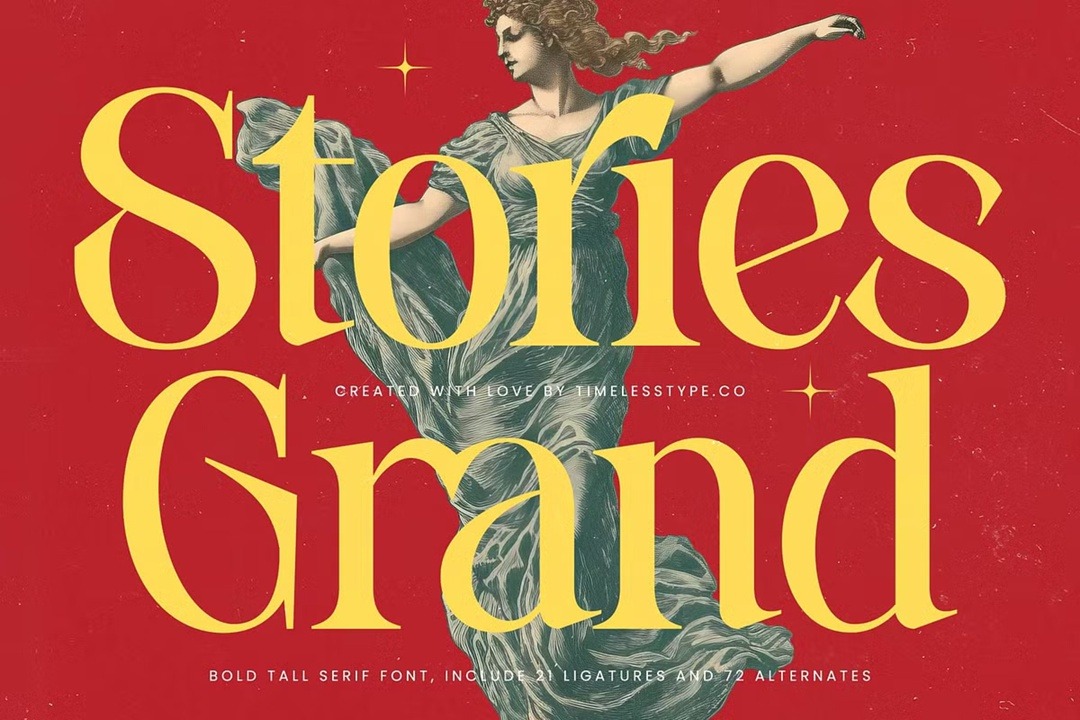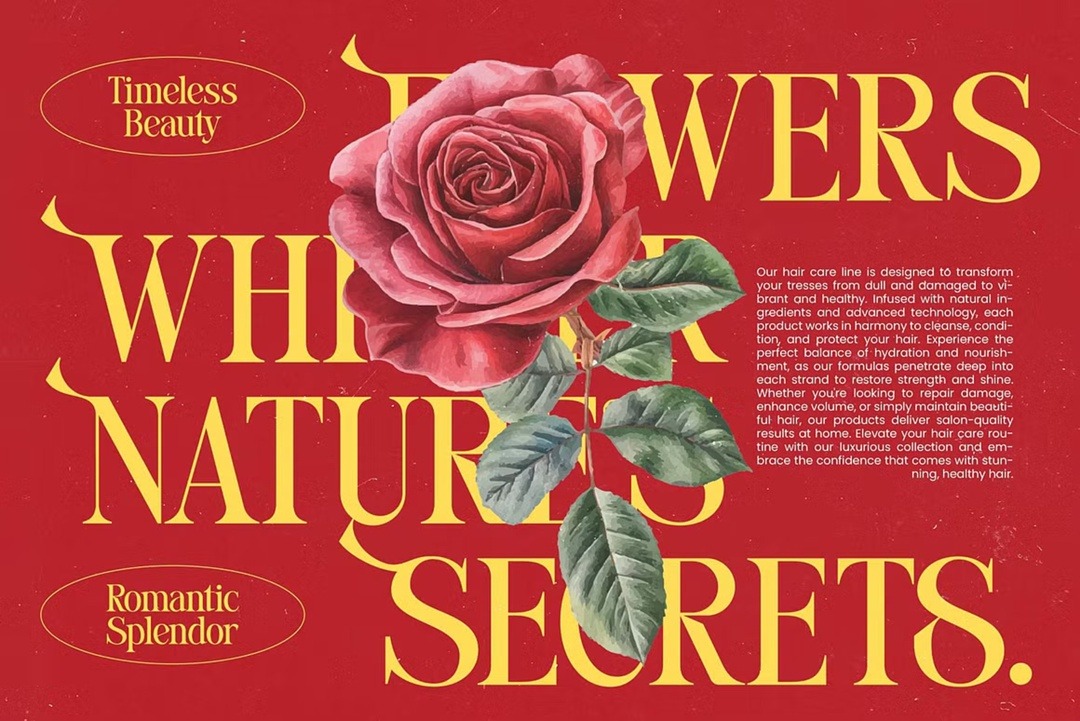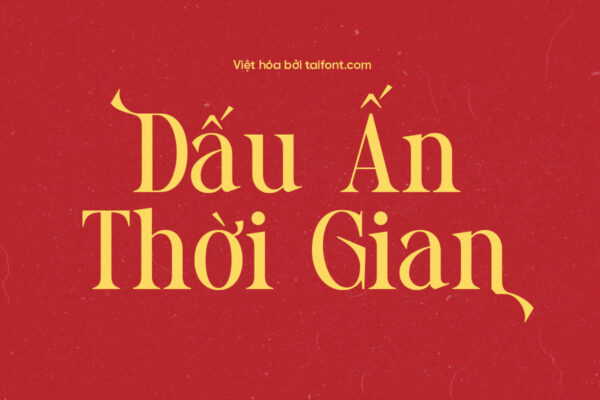
Giới thiệu về Font TF Stories Grand Việt hóa
TF Stories Grand Việt hóa là một font chữ có chân (serif) nổi bật với vẻ đẹp cổ điển, sang trọng và kho glyphs (ký tự đặc biệt) phong phú, đẹp mắt. Font này được thiết kế với những đường nét tỉ mỉ, đầy đặn nhưng vẫn giữ được sự tinh tế, gợi nhớ về phong cách typography vương giả của những thập niên vàng son. Sự đa dạng của các glyphs cho phép bạn sáng tạo không giới hạn, tạo nên những chi tiết độc đáo và cá nhân hóa.
Với phong cách đặc trưng và kho glyphs ấn tượng, Stories Grand là lựa chọn lý tưởng cho các ấn phẩm đòi hỏi sự đẳng cấp và hoài cổ:
- Thiết kế thời trang: Hoàn hảo cho các thương hiệu thời trang cao cấp, đặc biệt là những bộ sưu tập lấy cảm hứng từ phong cách cổ điển, hoàng gia. Font này sẽ giúp nhãn mác, lookbook, hoặc các ấn phẩm quảng bá toát lên vẻ tinh tế, sang trọng và đẳng cấp.
- Tạp chí cổ điển: Lý tưởng cho các tạp chí về lịch sử, nghệ thuật, văn hóa, hoặc thời trang vintage. Stories Grand giúp các tiêu đề, bài viết và bố cục trở nên cuốn hút, chuyên nghiệp và đầy chiều sâu, tái hiện hoàn hảo không khí của những ấn phẩm xưa.
Với TF Stories Grand Việt hóa, bạn có thể dễ dàng thổi hồn cổ điển đầy quyền quý và sự tinh tế vào các thiết kế, tạo ra những sản phẩm không chỉ đẹp mắt mà còn đầy cảm xúc và câu chuyện.